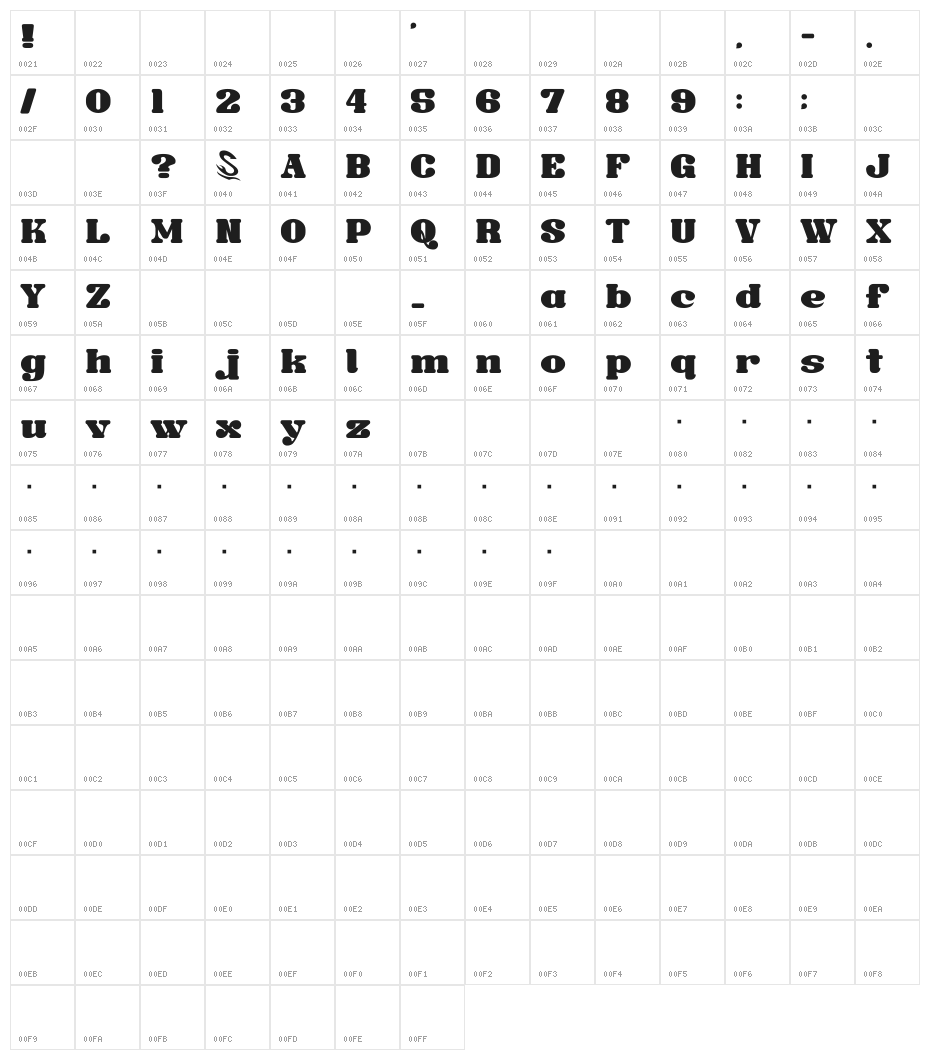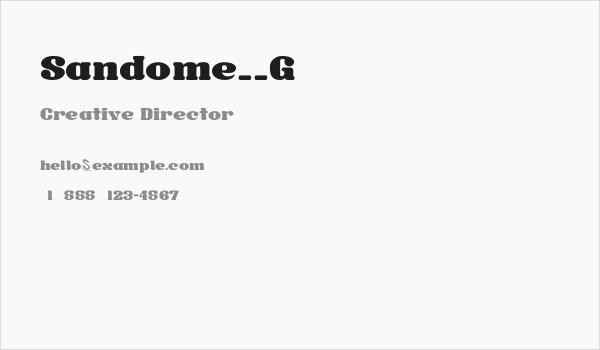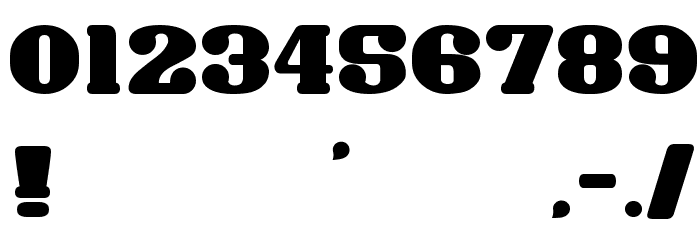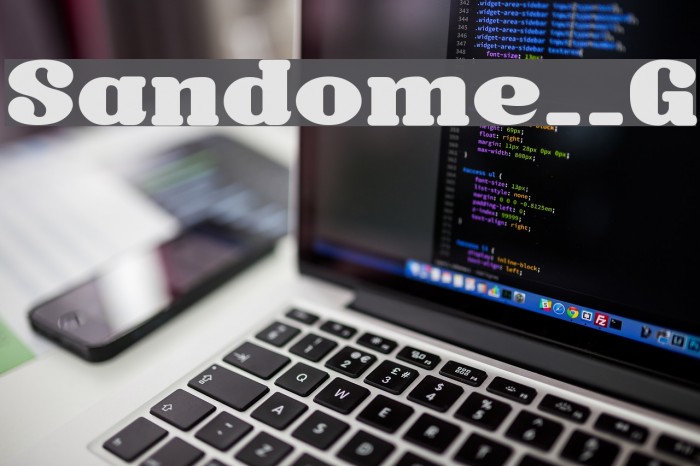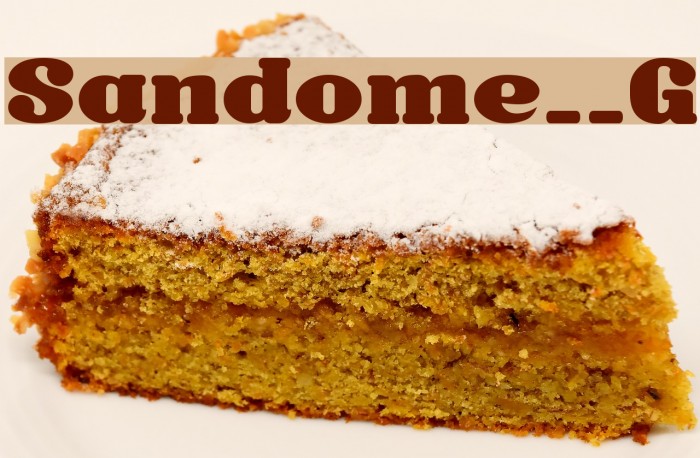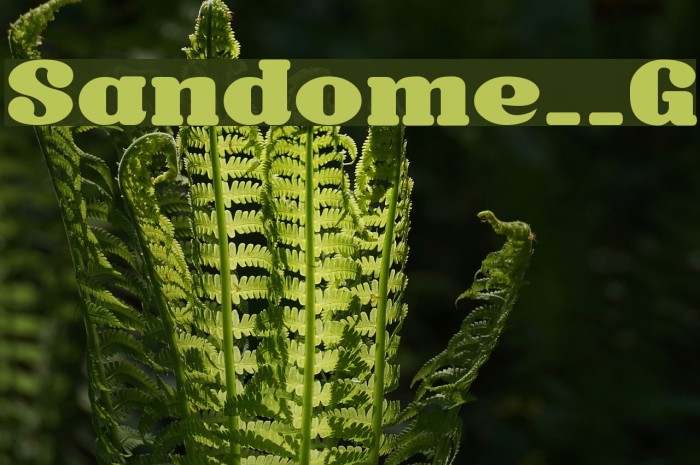
Sandome__G Font
| Общий стиль | Playful, Robust |
| Область применения | Headlines, Posters, Branding |
| Рекомендуемые проекты | Ideal for posters, headlines, branding, and any design that requires a strong, attention-grabbing typeface. |